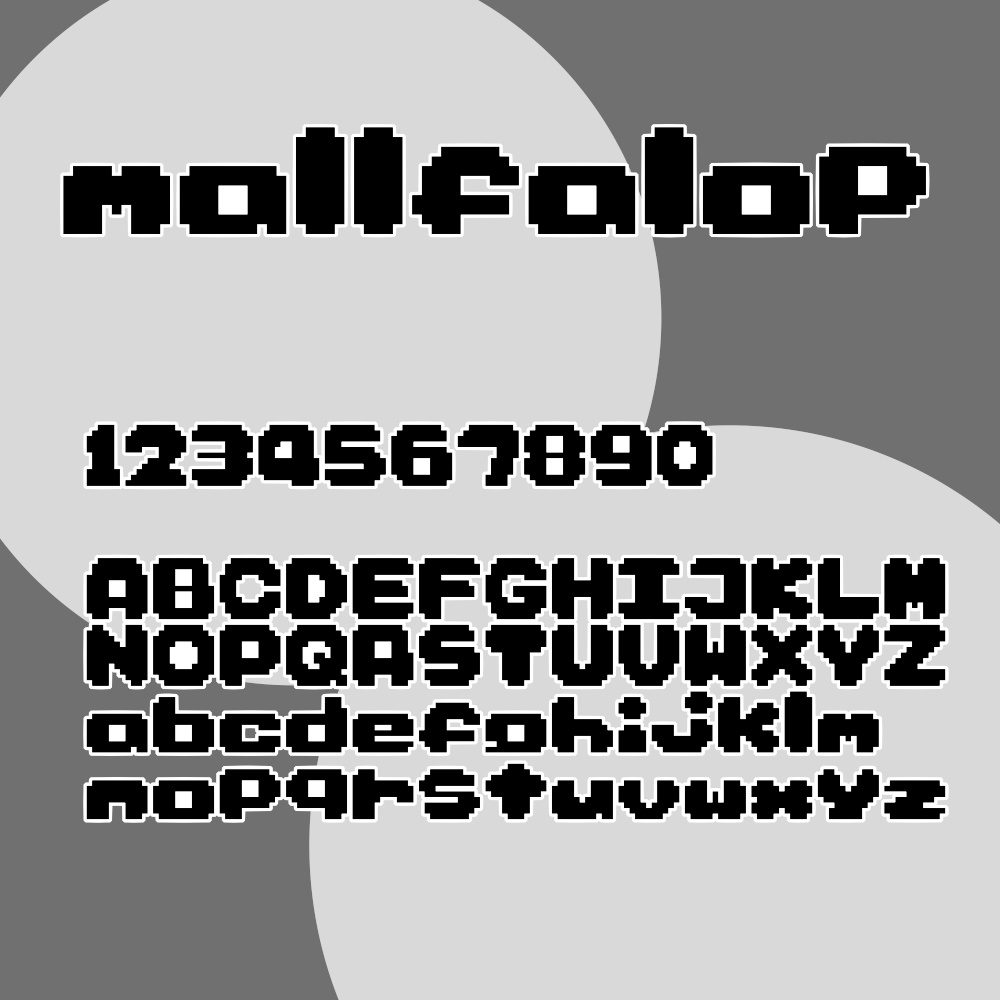
多忙のため事前に開けておきます。(〜R8.4.10まで配布予定) ______________________________ 毎年4/10&気が向いたとき&イベント時に配布しているフォントです。 ______________________________ 「マロファロップ(Qma-mallfalop.ttf)」は フォント作成について何も知らない触手(加熱九真/shokushuQ)が https://www.pentacom.jp/pentacom/bitfontmaker2/ さんの力によって、手打ちしてつくったドットのフォントです。 何も知らないので横書きのことしか考えていません。 ■利用範囲 個人利用、商用利用、ウェブフォントやゲームなど独自性のあるコンテンツへの組み込みは自由です。 年齢制限が必要なコンテンツにもご使用頂けます。 ■禁止事項 犯罪行為や違法行為への使用、改変前のフォントファイルを単独で再配布することは禁止します。 商標登録など、第三者が本フォントを使用できなくなる行為は禁止します。 ■改変と再配布 収録文字の8割以上を改変し、本規約を改変前フォントの規約として明記・同梱することで再配布可能です。 ■免責 本フォントの使用により生じた損害について、制作者(加熱九真/shokushuQ)は一切の責任を負いません。 ■その他 必須ではありませんが、使用の際にクレジット記載があると嬉しいです。 ■収録文字について 全角・半角ともに同じデザインです。 全角と半角のピクセル数が2:1ではありません。 全角スペースはかなり中途半端な幅です(修正方法模索中) 半角スペースを1ピクセル分にしてあるので、それでうまく調整してください。 ■全角 1234567890 ABCDEFGHIJKLMNOPQRSTUVWXYZ abcdefghijklmnopqrstuvwxyz ■半角 0123456789 ABCDEFGHIJKLMNOPQRSTUVWXYZ abcdefghijklmnopqrstuvwxyz